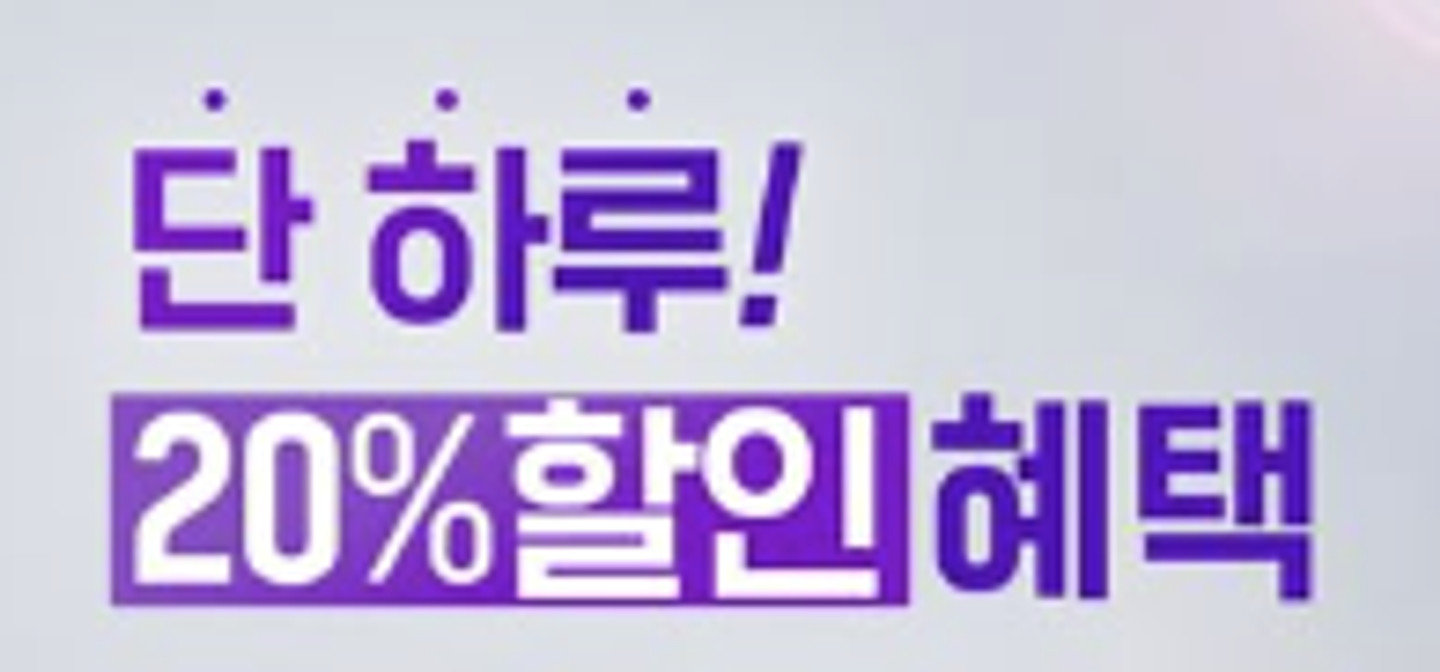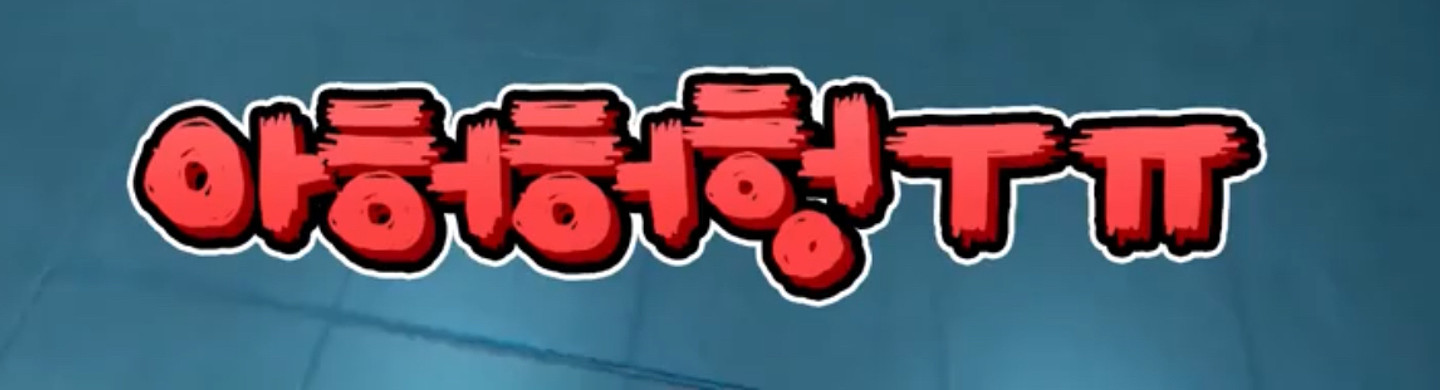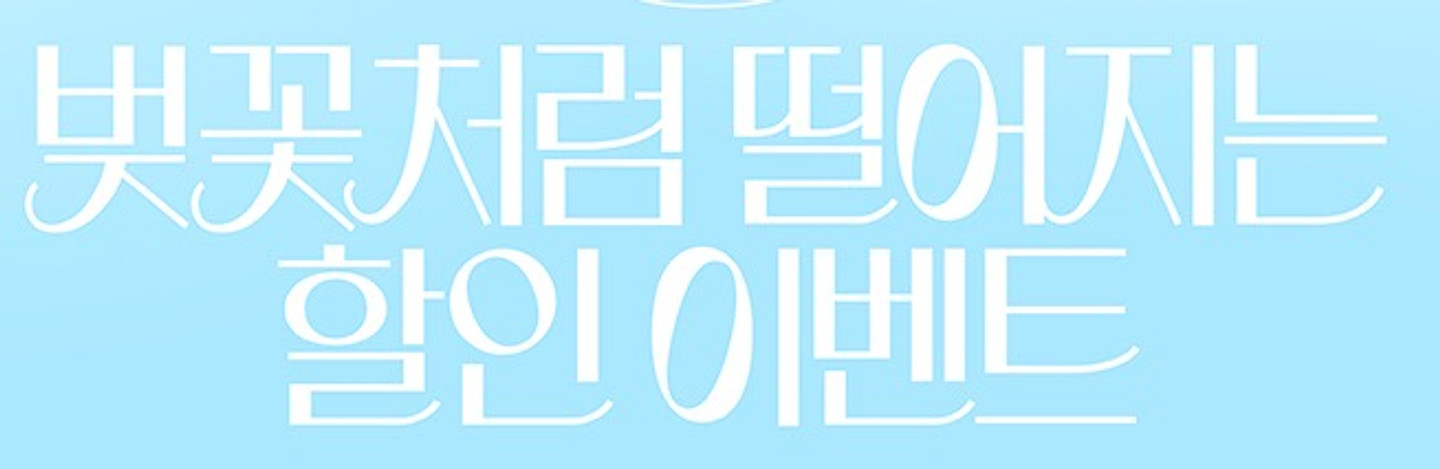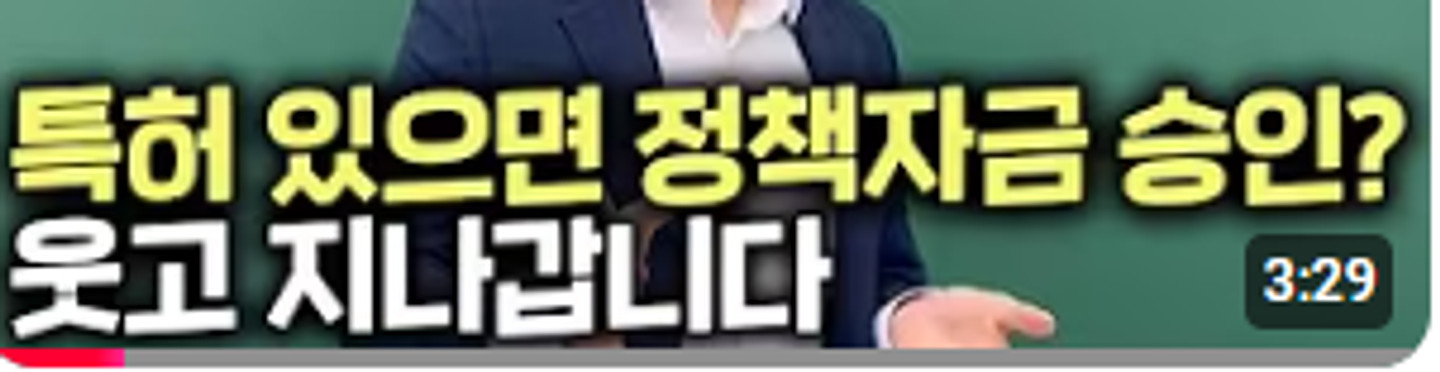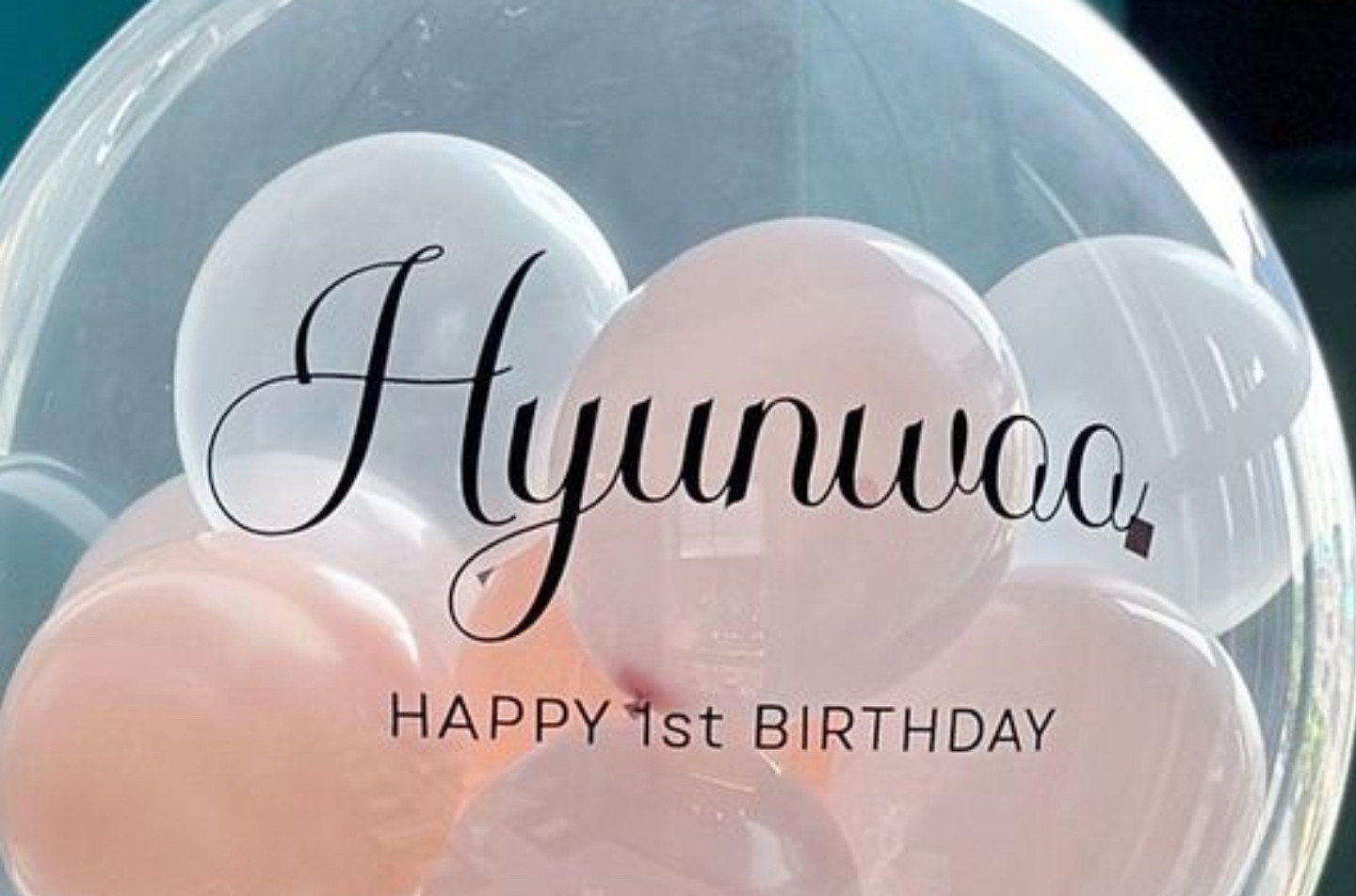
이거 직접 쓴 손글씨일까요? 폰트일까요?
sad
뭫까요??
눈누 고딕에서 찾았던거 같은데 초기화 하고 찾으려니 안보이네요
무슨 폰트인지 궁금합니다.
유튜브 아오니님 채널 자막 폰트가 궁금합니다!!
이거 폰트뭔가용
손글씨 같은 영어폰트고 아마 대문자로만 나왔던 것 같기도 해요ㅠㅠ 쓰던건데 기억이 안나요
폰트 뭐에여
이 폰트 궁금해요!
내용에 사용된 폰트 뭔지 알 수 있을까요?!
폰트가 궁금합니다ㅡ
이 폰트 뭔지 아시는분 ㅠㅠ
오옹
동글 네모한 폰트이름이 궁금해요
글씨체 폰트 제발 알려주세요 제발ㅠㅠ 몇년째 찾고있어요
이거 폰트 알려주실분...제발...ㅠㅠ부탁해여
큰 글씨 한달살기 성지 글씨체 알려주세요
이거 무슨 폰트인가요ㅠㅠ
영화 굿뉴스의 엔딩크레딧 폰트입니다!
폰트 찾아주세오
포브스 폰트 ㅜㅜ 비슷한거라도 찾아주세요
이거 폰트 뭔가요 ㅜ😿
무슨체 인지 알고 싶어요.궁금합니다.유토 무료폰트 중 하나는 아니죠??
무슨 폰트예요? 어디 앱에서 찾을 수 있어요?
해당 글꼴이 궁금합니다. :(
폰트뭘까요!
폰트뭘까요?
어느 블로그에서 보고 괜찬아서 찾아 봤더니 이런 폰트였어요. 혹시 아시는 분 계실까요? 비슷한 폰트 추천도 좋습니다. ^^
아무리 봐도 도저히 모르겠는데 이거 무슨폰트인지 아시나요??
꼭 그럴 필요 있어? 폰트 부탁드립니다 오랜만에 맘에 드는 폰트 발견했는데 뭔지 모르겠습니다..
소담소담 폰트궁금합니다.
이 폰트 무슨 폰트에요 ? ㅜㅜ 알려주세요 ㅜㅜ
이 폰트 알 수 있을까요..ㅠㅠ
20231015 숫자랑 HEESEUNG 폰트 아시는분,,
무슨 폰트인지 아시는 분 계신가요?
이 폰트좀 알려주세요..
이 폰트좀 알려주세요 !!!
영문 필기체 폰트 궁금해요 ㅠㅠ!!!!!
이 폰트 진짜 알고 싶어요 ㅜㅜ
이 폰트 뭔지 아시는분 ㅠㅠ!
혹시 이 폰트가 뭐인지 아시는 분 있나요..?
폰트에 대해 잘 몰라서 ㅠㅠ 무슨 폰트인지 알수있을까요 ? !!! ㅠㅠ 답변해주시면 감사하겠습니다 !
무슨 서체 일까요?
이 글씨체 뭔지 아시는 분 계실까요
영화 화양연화 포스터 글씨체 뭔지 아시는분 계시나요 ㅜㅜ
폰트 이름 알려주세요..ㅠ.ㅠ
고수님들 해당 폰트가 궁금합니다ㅜㅜ
고수님들 부탁드립니다. 이거 무슨 폰트인가요? 비슷한 폰트라도 알려주세요. 제발요~~
마인크래프트 서버에 사용되던 폰트 입니다 약 7년 정도 된 걸로 알고 있습니다
무슨폰트인지 궁금합니다~~